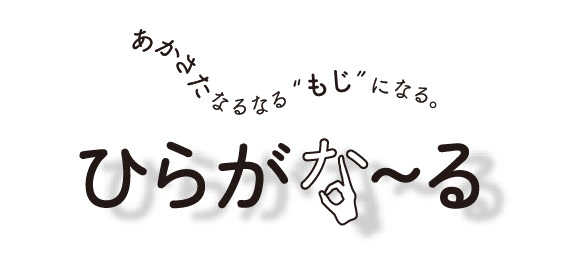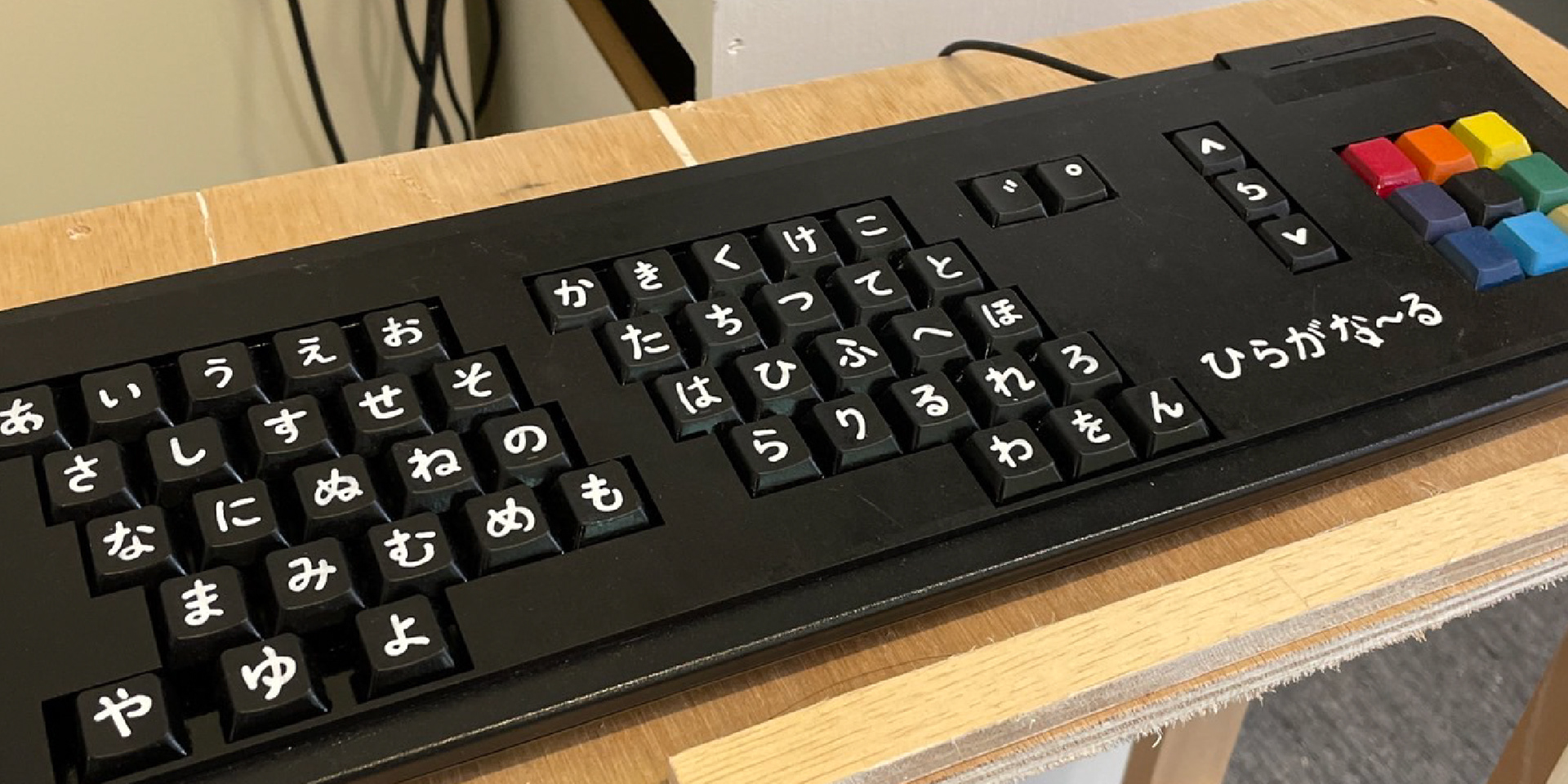
ひらがな〜る
投影されたひらがなの一部を体験者が補いひらがなを完成させる体験型アート作品です。体験者の手のシルエットからひらがなの足りない部分を生成します。投影するひらがなの選択には、ひらがなのみが書かれた専用の「ひらがなキーボード」を使用します。
concept
欠けた文字をにどのようにして完成させるかを考えさせること。また、体験者自身が完成させた文字に親しみを持ってもらうことを狙いとしています。文字の補填には「手」を使うことを想定していますが、腕などの別の身体部位、道具などを使用するなど、体験者に柔軟に文字を作ることを楽しんでもらいたいです。また、1人で文字を完成させることが困難な場合は、複数名で協力するなど自由に楽しめます。
product
ひらがなを覚えたこどもをメインターゲットとしています。そのため操作は理解しやすく複雑でないことが重要と考え、文字を入力するために「ひらがなキーボード」を制作しました。キーの1つ1つにひらがな1文字を対応させ、「ひらがなキー」が押されるとそのひらがな(の一部)が投影されるようにプログラムしています。また、子供と大人で体の大きさが異なるため文字の大小を変更できるキーと、体験者がオリジナルの文字を作り写真を撮ることを考慮し背景色を変更できるキーを用意しています。